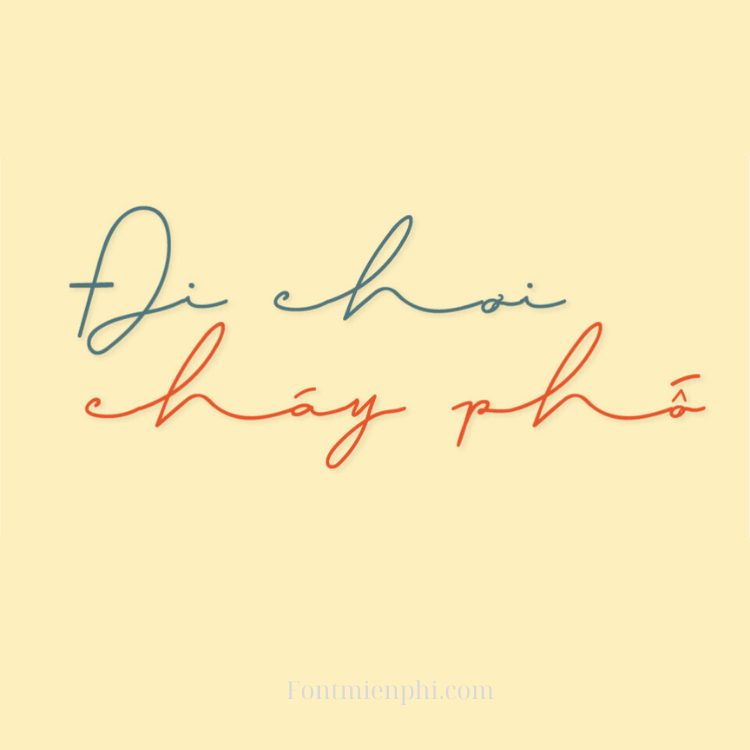
Font Việt hóa VIP The Yoshi
Font Việt hóa VIP The Yoshi – Đỉnh Cao Thiết Kế Sáng Tạo Cho Học Đường
Giới thiệu về bộ Font Việt hóa VIP The Yoshi
Trong thế giới đồ họa hiện đại, việc lựa chọn một bộ Font Việt hóa VIP The Yoshi phù hợp chính là chìa khóa để tạo nên sự khác biệt. Đối với các bạn học sinh và giáo viên, Font Miễn Phí không chỉ giúp bài thuyết trình thêm sinh động mà còn truyền tải thông điệp một cách chuyên nghiệp. Bộ chữ này sở hữu những đường nét thanh thoát, hiện đại nhưng vẫn giữ được nét gần gũi, giúp người xem dễ dàng tiếp nhận nội dung trong các tài liệu giáo dục hay dự án cá nhân.
Những đặc điểm nổi bật của Font Việt hóa VIP The Yoshi
Tính ứng dụng linh hoạt trong học tập
Font Việt hóa VIP The Yoshi nổi bật nhờ khả năng hiển thị rõ nét trên cả màn hình kỹ thuật số và bản in. Các ký tự được tinh chỉnh tỉ mỉ, hỗ trợ đầy đủ dấu tiếng Việt, giúp tránh các lỗi hiển thị phổ biến. Đây là lựa chọn hoàn hảo cho việc thiết kế bìa báo tường, làm slide bài giảng hoặc trang trí sổ tay học tập. Sự kết hợp giữa phong cách tối giản và tinh tế giúp bộ font này chiếm trọn cảm tình của cộng đồng thiết kế tại Việt Nam.
Vẻ đẹp thẩm mỹ và phong cách độc đáo
Với cấu trúc hình học hài hòa, bộ font này mang lại cảm giác cân đối và dễ nhìn. Khi sử dụng trong các sản phẩm truyền thông của nhà trường, nó tạo ra vẻ ngoài chỉnh chu và hiện đại. Bạn có thể dễ dàng phối hợp Yoshi với các phông nền màu sắc khác nhau để tạo ra những hiệu ứng thị giác ấn tượng nhất.
Kết luận về bộ phông chữ chất lượng cao